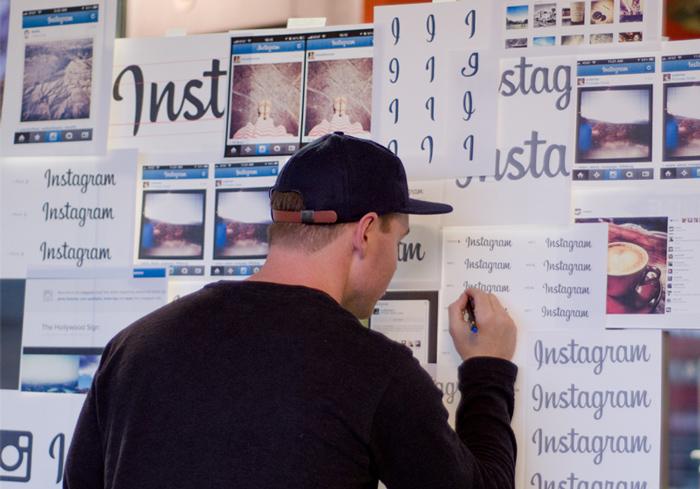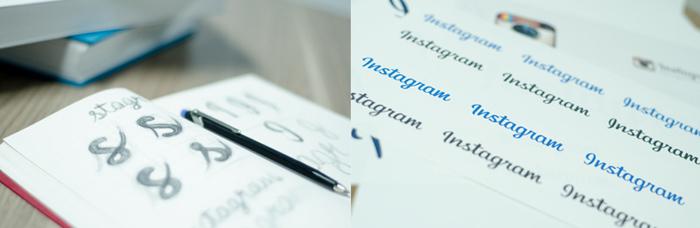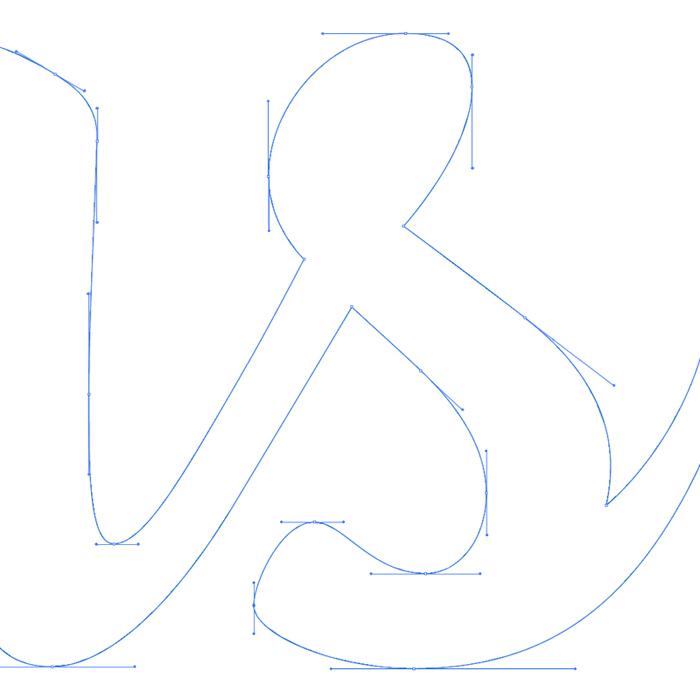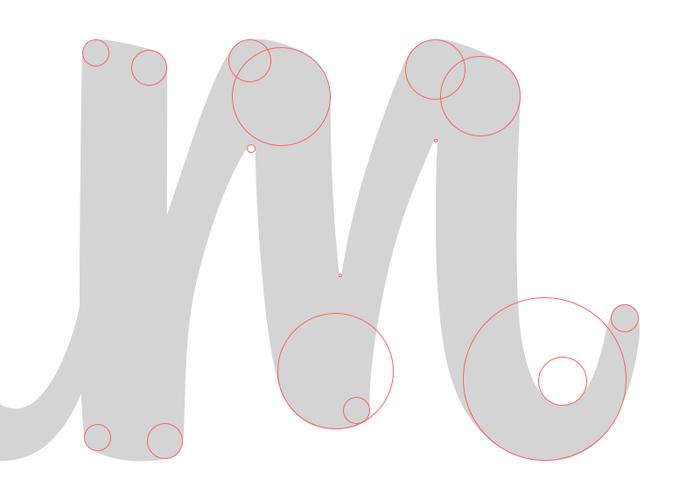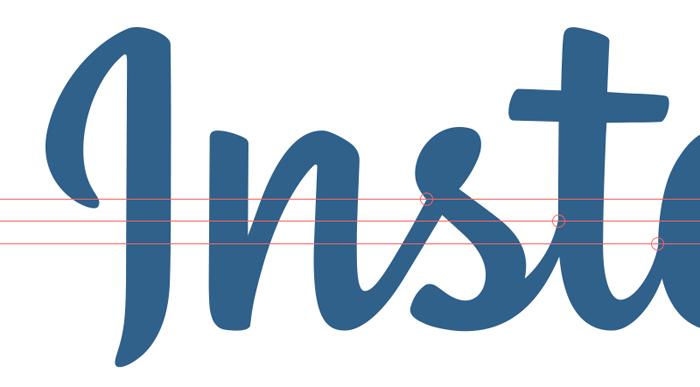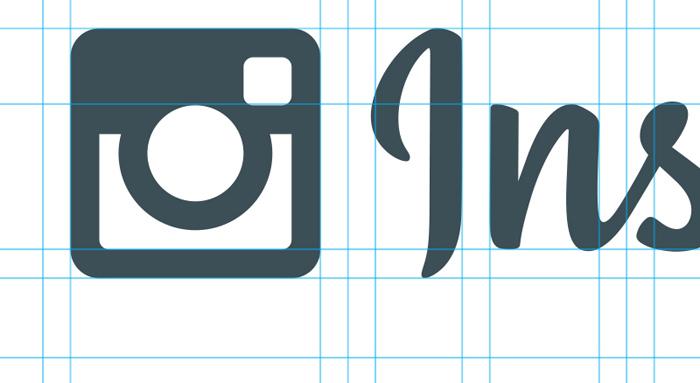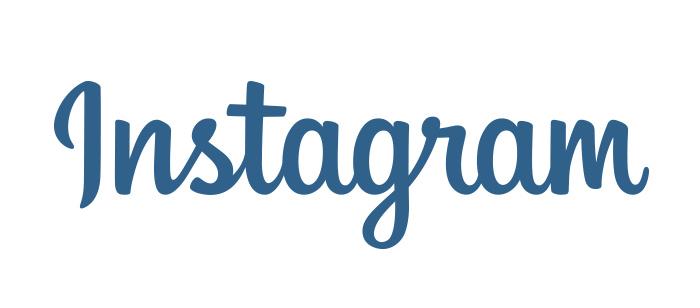
Die Foto-App Instagram ist eine der beliebtesten Anwendungen, die speziell für Mobiltelefone entwickelt wurden. Vor nur 3 Jahren erstmals erschienen, hat die Anwendung mittlerweile schon über 100 Millionen Nutzer und wurde 2012 für 1 Milliarde US-Dollar von Facebook übernommen. Mit der gerade erschienenen Version 3.5 wurde das bekannte Logo typografisch überarbeitet.
Das alte Logo
Wie das markante Icon von Instagram hat auch der Schriftzug einen Retro-Charakter, der auf den amerikanischen Hand-Lettering-Stil Mitte des 20. Jahrhunderts anspielt. Gesetzt wurde das Logo aus der 2006 erschienenen Billabong von Type Associates.
Das Logo wurde aber tatsächlich nur aus dieser Schrift gesetzt und nicht als Wortmarke entwickelt. Und so wirken insbesondere die Buchstabenverbindungen nicht so optimal, wie es bei einem Schreibschrift-Logo möglich wäre. Mit der Überarbeitung sollte dies nun verbessert werden. Von Instagram heißt es dazu:
“The brief was simple, the process long. Our main aim was to make our logotype look more refined and mature. But with a logotype with so much brand recognition, it's hard to stay objective.”
Das neue Logo sollte also lediglich eine Überarbeitung darstellen. Verantwortlich für den Entwurf zeichnet der amerikanische Designer Mackey Saturday. Und so sieht das neue Logo aus:
Das neue Logo ist nun eine echte Schreibschrift-Wortmarke mit harmonisch verbundenen Buchstaben. Das Ziel des Briefings wurde sicherlich erreicht. Das Logo wirkt nun »erwachsener«, klarer und ist leserlicher. Allerdings ging auch ein Teil des markanten Retro-Stils des Originals verloren – etwa die »tanzende« x-Höhe, die dem alten Logo ein auffälliges Wortbild verlieh. Nun wirkt das Logo deutlich glatter und vielleicht auch etwas zu glatt.